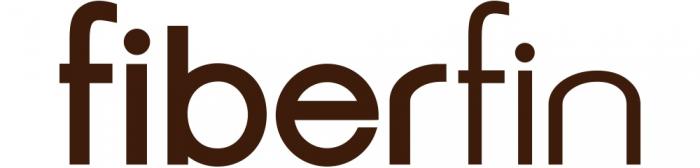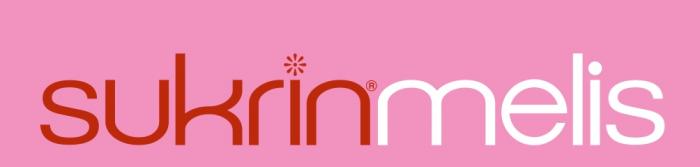
Schrift mit "markantem k"
ich würde folgende Schrift suchen (sofern es überhaupt eine Schrift ist...):
Die Schrift wird in den Produktbezeichnungen von "www.sukrin.org" verwendet - und das norwegische "Kakemix" lässt sich im deutsch-sprachigen Raum schlecht verkaufen - daher muss ich die Titel abändern... :-)
(der i-punkt bei Sukrin ist klarerweise getauscht)